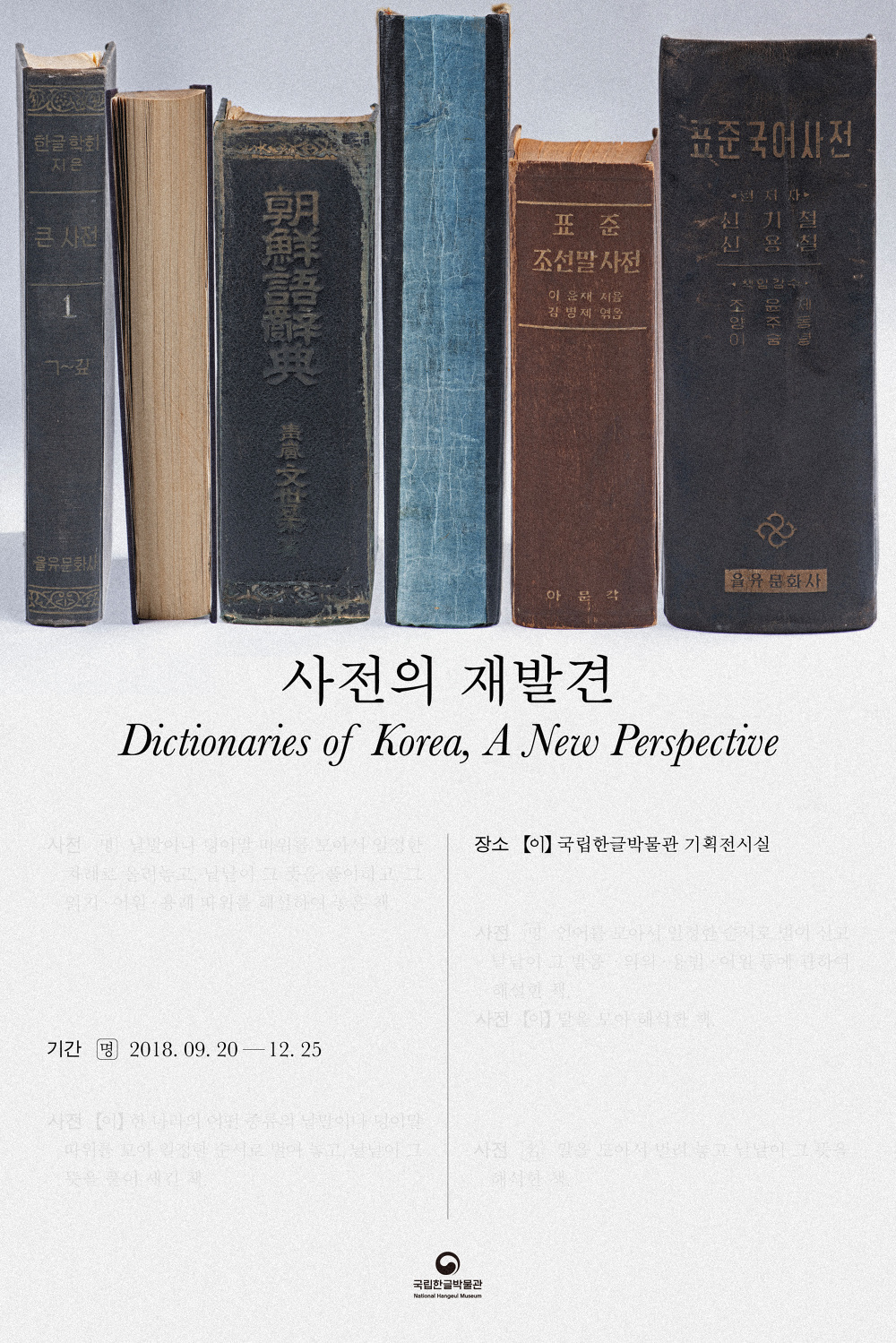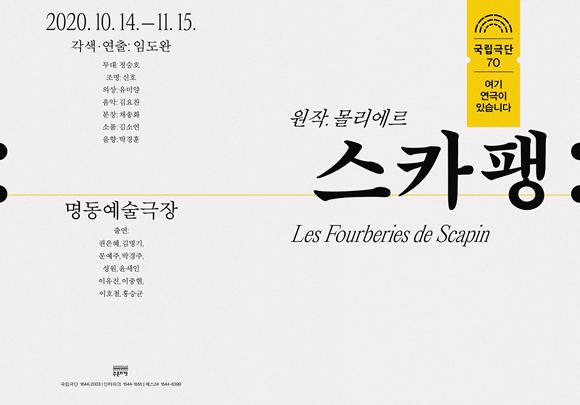
Q. SM폰트와 라틴 알파벳폰트와의 페어링 중 가장 좋아하는 조합은?
이번 연말 작업에 세명조를 사용하는 일들이 많았는데, 세명조와 Restora Neue extra light를 많이 섞어썼다.
얇은 펜촉 혹은 붓으로 쓴듯한 필기구의 느낌이 남아있는 서체들이라고 생각했고, 두 개의 폰트 조합만으로도 지면이 우아해지는 느낌을 받았다.
Q. SM클래식 시리즈 중 가장 좋아하는 서체는 무엇입니까?
sm클래식 시리즈 중 가장 좋아하는 서체는, sm견출명조이다.
본문 조판할 때도 많이 쓰지만, 특히나 포스터와 같이 큰 사이즈의 이미지에 적용할 때도 클래식한 느낌을 가지면서도 형태적인 재미가 많은 글자라고 생각한다.
Q. SM폰트를 사용해 만든 개인작업이 있나요?
2019-2020 국립극단의 모든 인쇄물의 매뉴얼 작업을 페이퍼프레스에서 진행했다.
인쇄물에 사용되는 모든 서체는 견출명조와, 신신명조, 중고딕으로 전부 SM클래식 서체를 사용했다.
Q. SM폰트를 사용해 만든 작업중 가장 기억에 남는 작업은?
이번 국립중앙박물관 [한겨울지나 봄오듯] 특별전에 세명조를 사용했다.
세명조를 공간과 같은 큰 사이즈의 작업에 적용했던 경우는 처음이었는데, 확대해서 보니 새삼스럽게 세명조의 획 하나하나가 굉장히 단아하고 예뻐 보였다. 특히 ㅎ과 같은 특정 자음이 붓글씨스러운 조형을 가지고있어서 들여다보는 재미가 있었다.
Q. SM폰트 앞으로 이렇게 진화했으면 좋겠다?
한글 서체의 더 다양한 선택지를 제공하는데 일조해줬으면 좋겠다. 본문 조판에 용이한 완성도 높은 서체들이 더 많이 나왔으면한다.
[SM세명조]
국립중앙박물관 특별기획전 <한겨울 지나 봄 오듯 - 세한, 평안>, 전시공간 그래픽디자인 ∙ 2020
[SM3신신명조]
국립한글박물관, <사전의 재발견> 포스터, 전시 ∙ 2018
[SM3견출명조, SM3신신명조]
<국립극단 2019-2020 공연 그래픽 아이덴티티> , 홍보물 ∙ 2019